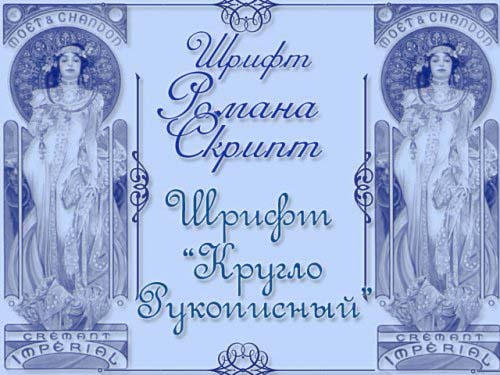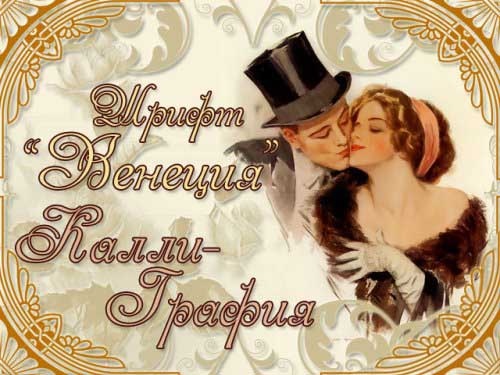
Винтажные русские шрифты Часть 1
нет цифр. Т.к. отрисовывалось с книги. Итак, в папку входят:
Elzevir- Эльзевир (знаки препинания есть, цифер нет)
Old Classic- Старая Классика (знаки препинания и цифры есть)
Pompadur- Помпадур (знаки препинания и цифры есть)
Redinger- Редингер (знаки препинания и цифры есть)
Romana Script- Романа скрипт (знаки препинания и цифры есть)
Round Script- Круглорукописный (знаки препинания и цифры есть)
Script Thin pen- Скрипт Тонкое перо (знаки препинания и цифры есть)
Venecia- Венеция (знаки препинания некоторые есть, цифер нет)
Roland-Decor Роланд Декор (знаки препинания и цифры есть)
Tchekhonin1 Буквицы (рисунки в древнеруском стиле) Чехонин1 (только буквицы)
Tchekhonin2 Буквицы (рисунки в каллиграфическом стиле) Чехонин2 (только буквицы)
Zaglavny- Заглавный (знаки препинания некоторые есть, цифер нет)